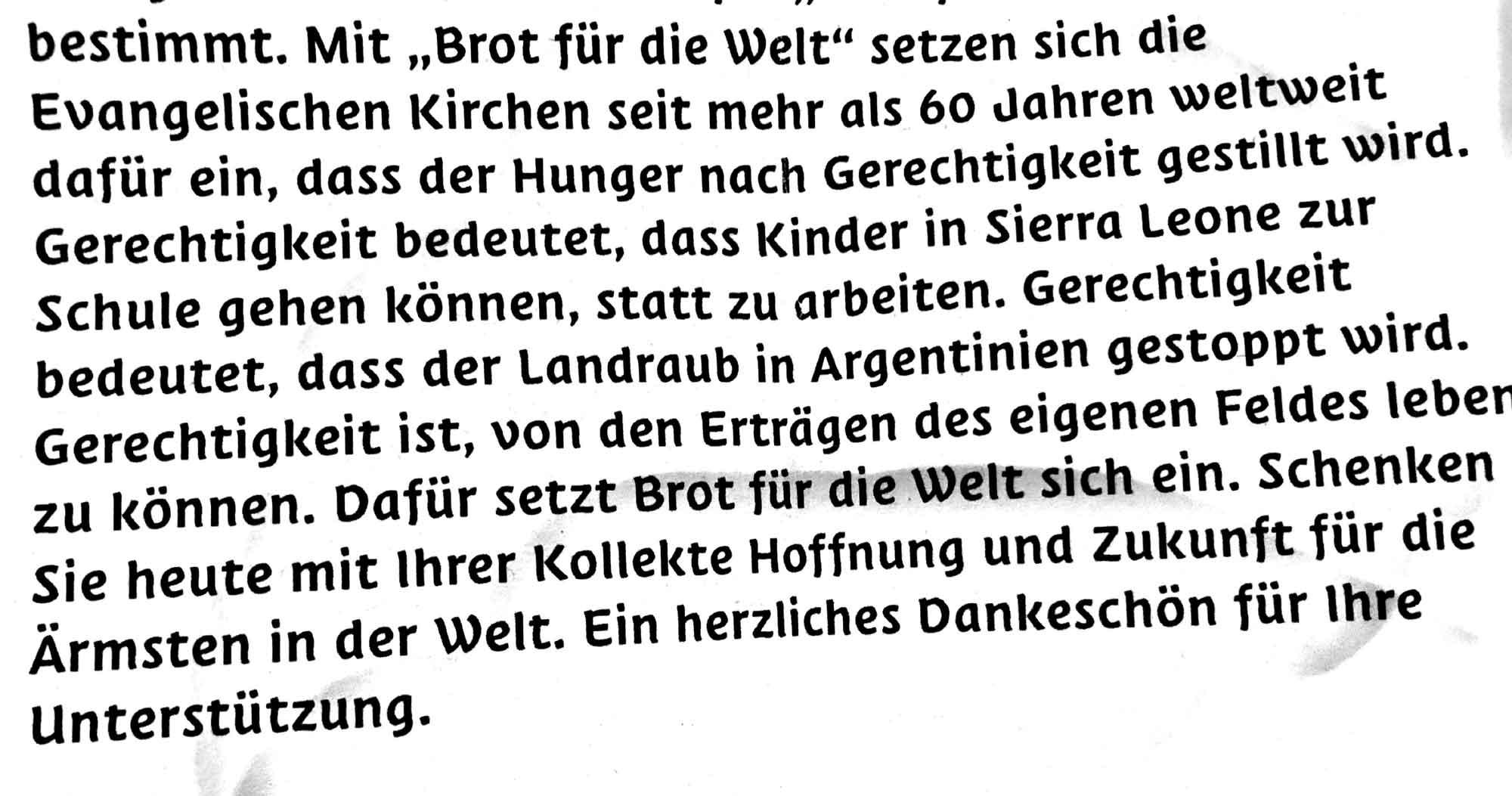
Schrift aus Aktuellem Liedblatt gesucht
Ich suche eine Schriftart aus einem Liedblatt, dass ich über Weihnachten in der Hand hatte. Besonders das w finde ich auffällig, aber kein online Tool identifiziert den Font.
das erinnert mich irgendwie an die Suedtirol Pro ...
Dann Elemente der Dachmarke -> Schriftfamilie
Da werden aber nur wenige Buchstaben gezeigt. Das hier ist besser:
Gleich der zweite Eintrag nach der Bundessans und Bundesserif zeigt die Suedtirol Pro.